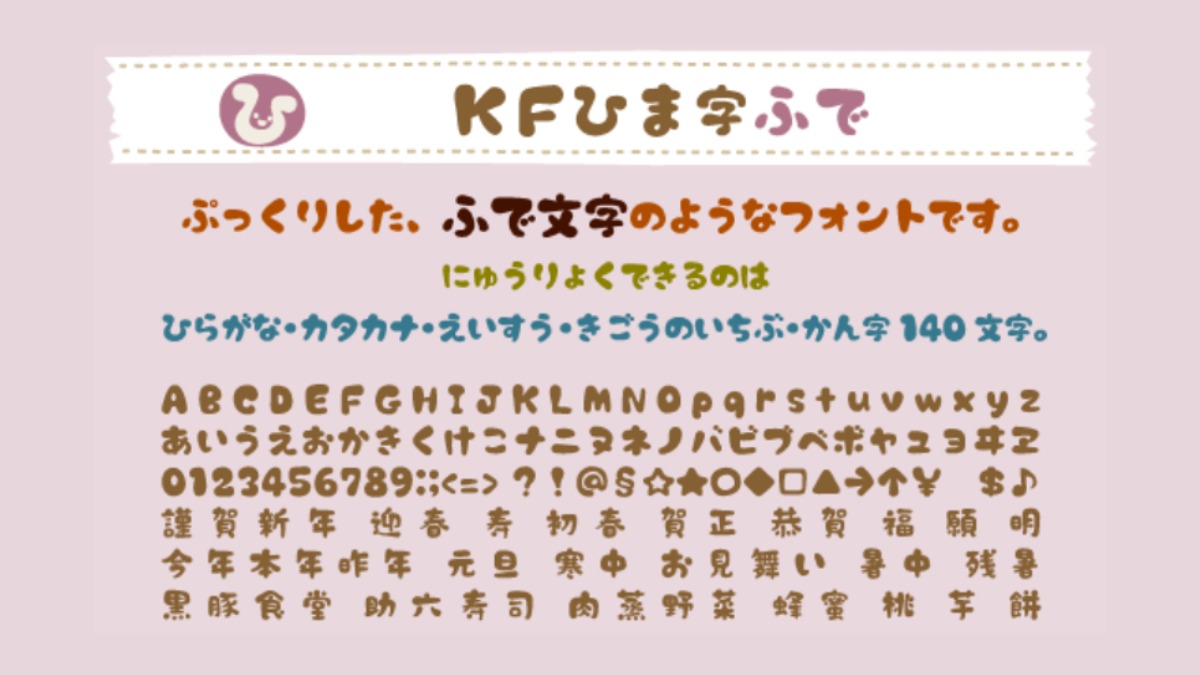
KFひま字ふでは、ぷっくりとした筆文字のようなかわいらしい日本語フリーフォントです。太めの文字なので見出しやタイトルに向いているフォントです。
KFひま字ふでの詳細情報
| 書体名 | KFひま字ふで |
| 書体 | デザイン書体 |
| 収録文字 | アルファベット カタカナ ひらがな 数字 漢字 記号 |
KFひま字ふでは、ぷっくりとした筆文字のようなかわいらしい日本語フリーフォントです。太めの文字なので見出しやタイトルに向いているフォントです。